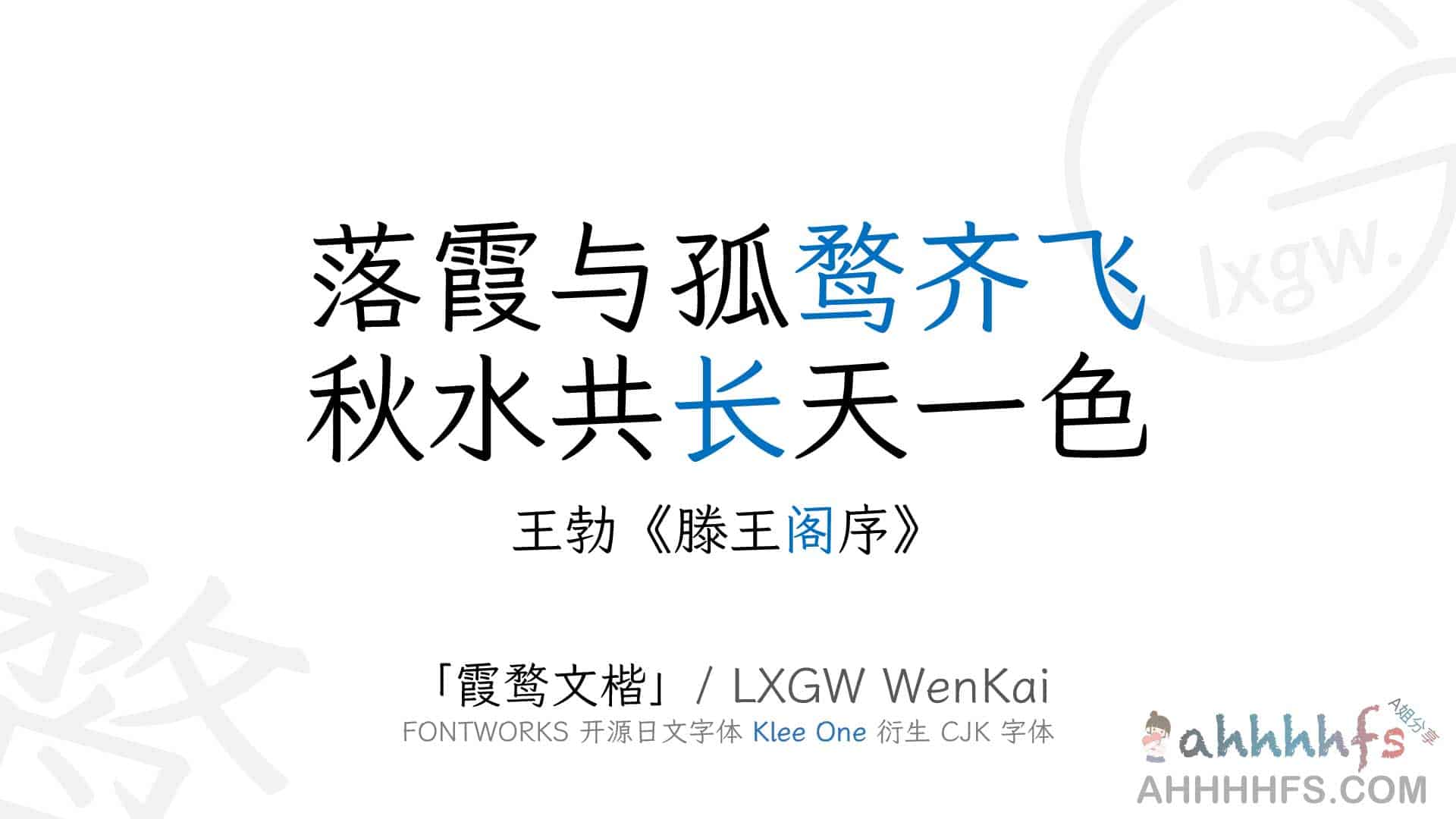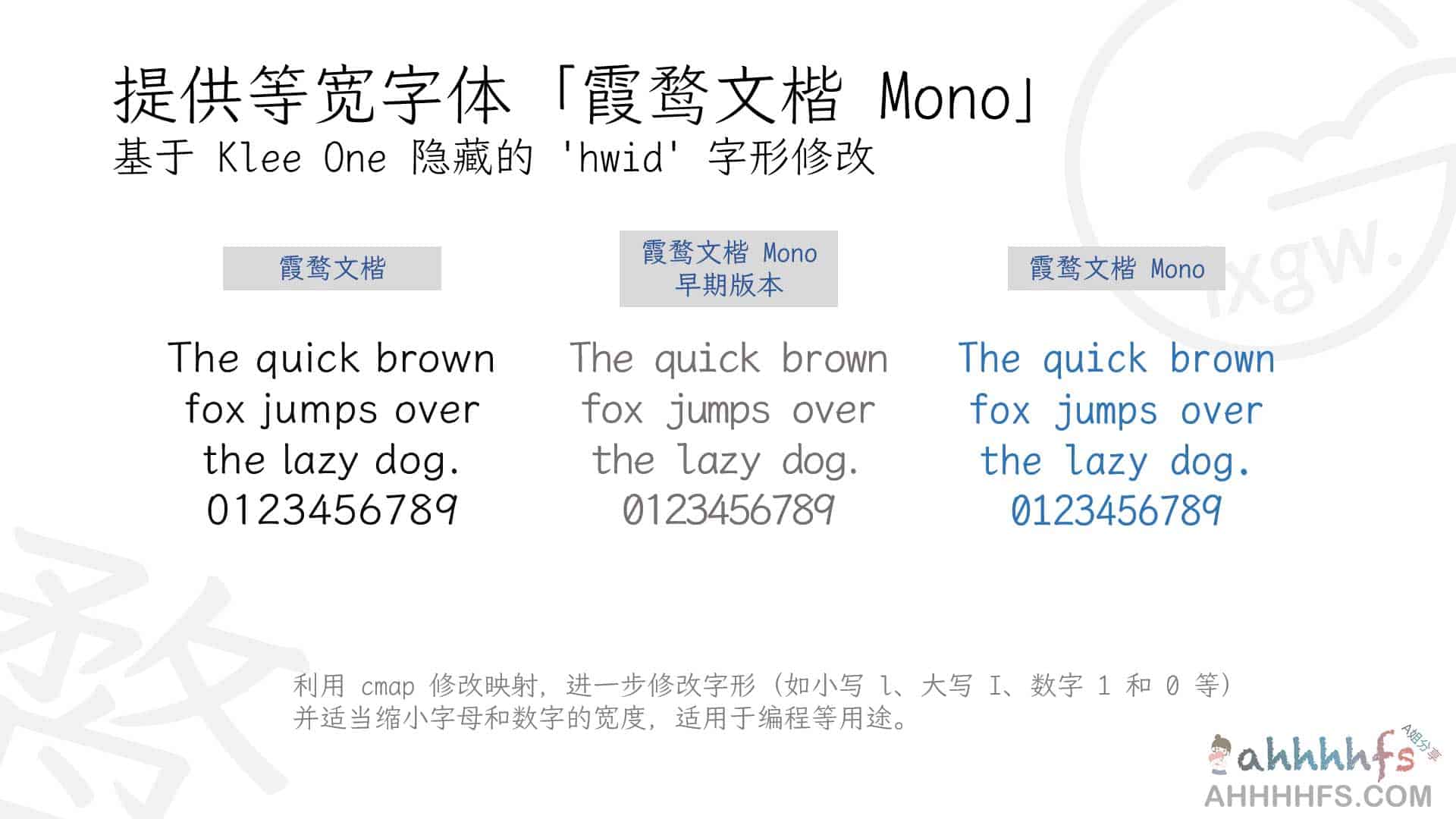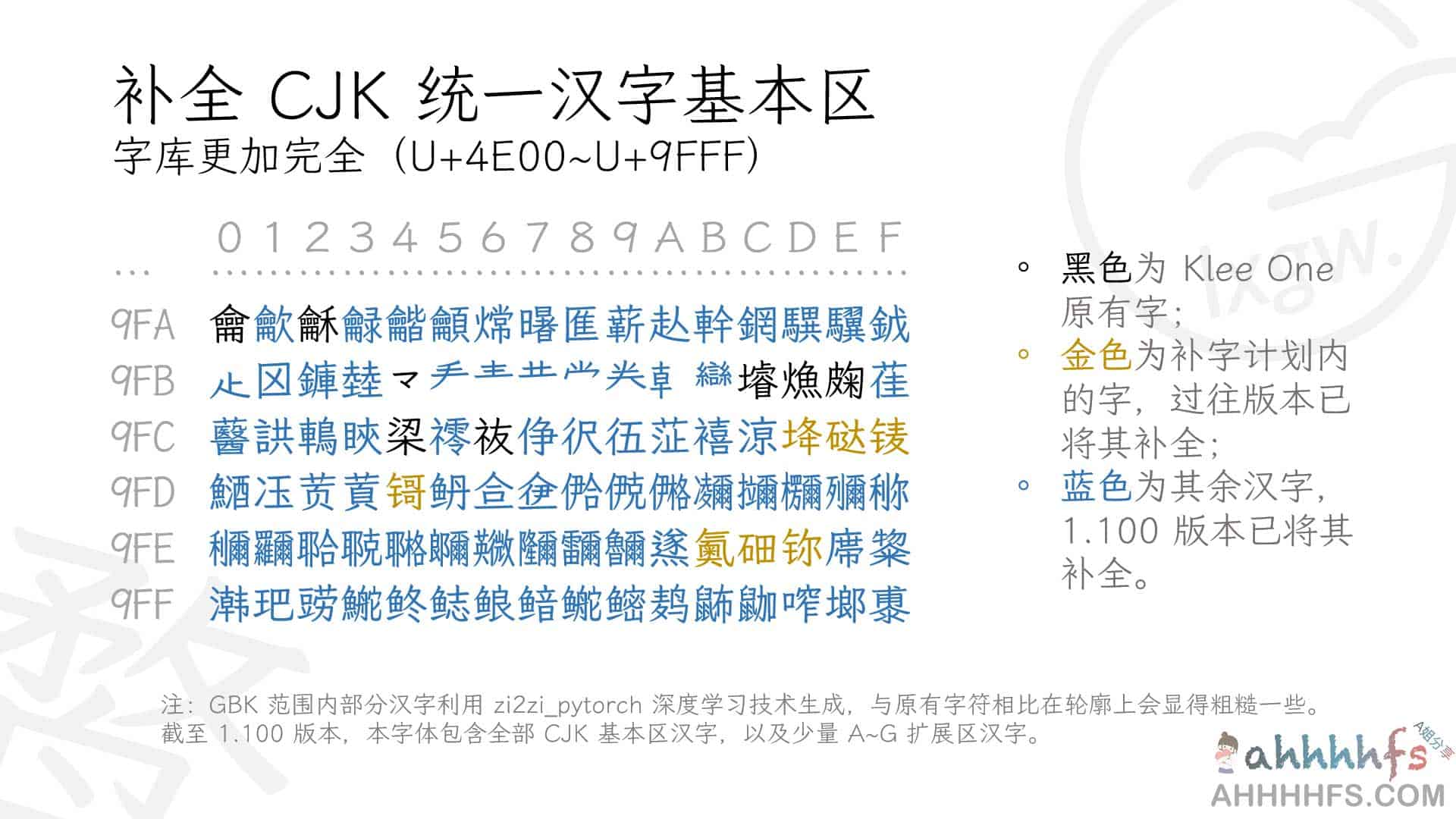
霞鹜文楷 (LxgwWenKai) 开源中文字体
霞鹜文楷 是一款基于 Fontworks 旗下的 Klee One 衍生而来的开源中文字体。它在保留原日文字体风格的基础上,大规模补全了简繁体中文、港台异体字、粤闽客方言字以及注音符号,并实现了对韩朝语的支持。全库涵盖简繁日汉字 2 万余字,基本解决了缺字问题,且完全 免费可商用
设计特点与演进
该字体呈现出鲜明的日本教科书体风格,融合了楷体与仿宋的特质,具备极高的可读性。在早期的社区实践中,许多爱好者尝试通过商业仿宋字体补全 Klee One 以用于 iOS 或 Android 系统美化,但这带来了两个核心痛点:一是补全字体与原字之间存在视觉差异,混排时违和感强;二是商业字体的引入导致整体失去了商用权限,存在侵权风险。
为了填补开源社区中楷体与仿宋类字体的空白,霞鹜文楷在 2021 年正式启动补全计划。为了优化阅读体验,开发者特意将原版的 SemiBold 字重选定为 Regular 字重,使其在正文排版中更具质感。目前,该字体已演进为支持简繁日韩的 3 字重字体家族。
适用场景
由于其出色的可读性和温润的笔触,霞鹜文楷非常适合用于以下场景:
• 电子书 / 长文阅读:替代传统的宋体或楷体,减轻视觉疲劳。
• 系统美化:适用于 Android/iOS 等移动端系统的字体替换。
• 商业设计:得益于开源协议,可放心用于商业海报、UI 界面及出版物。